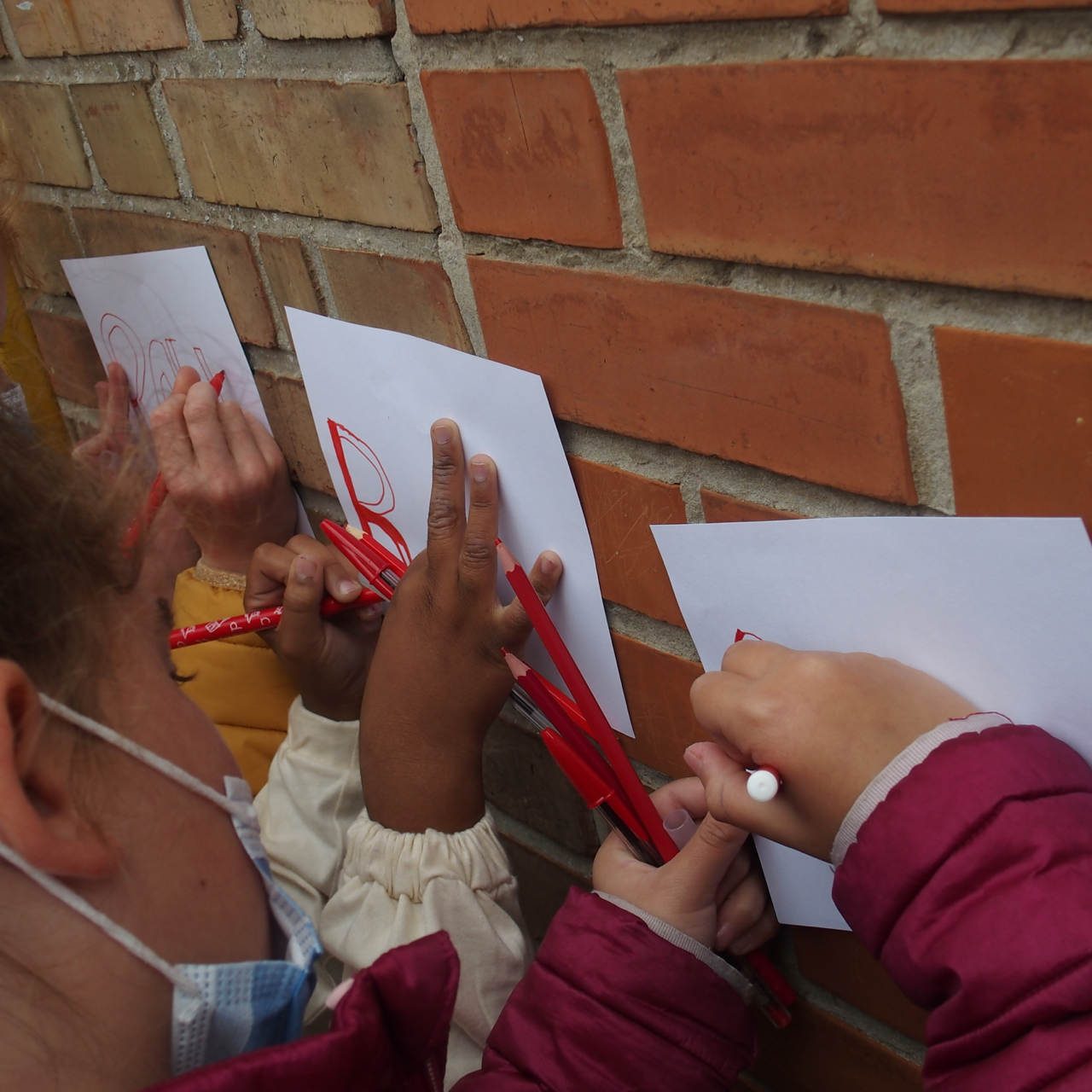
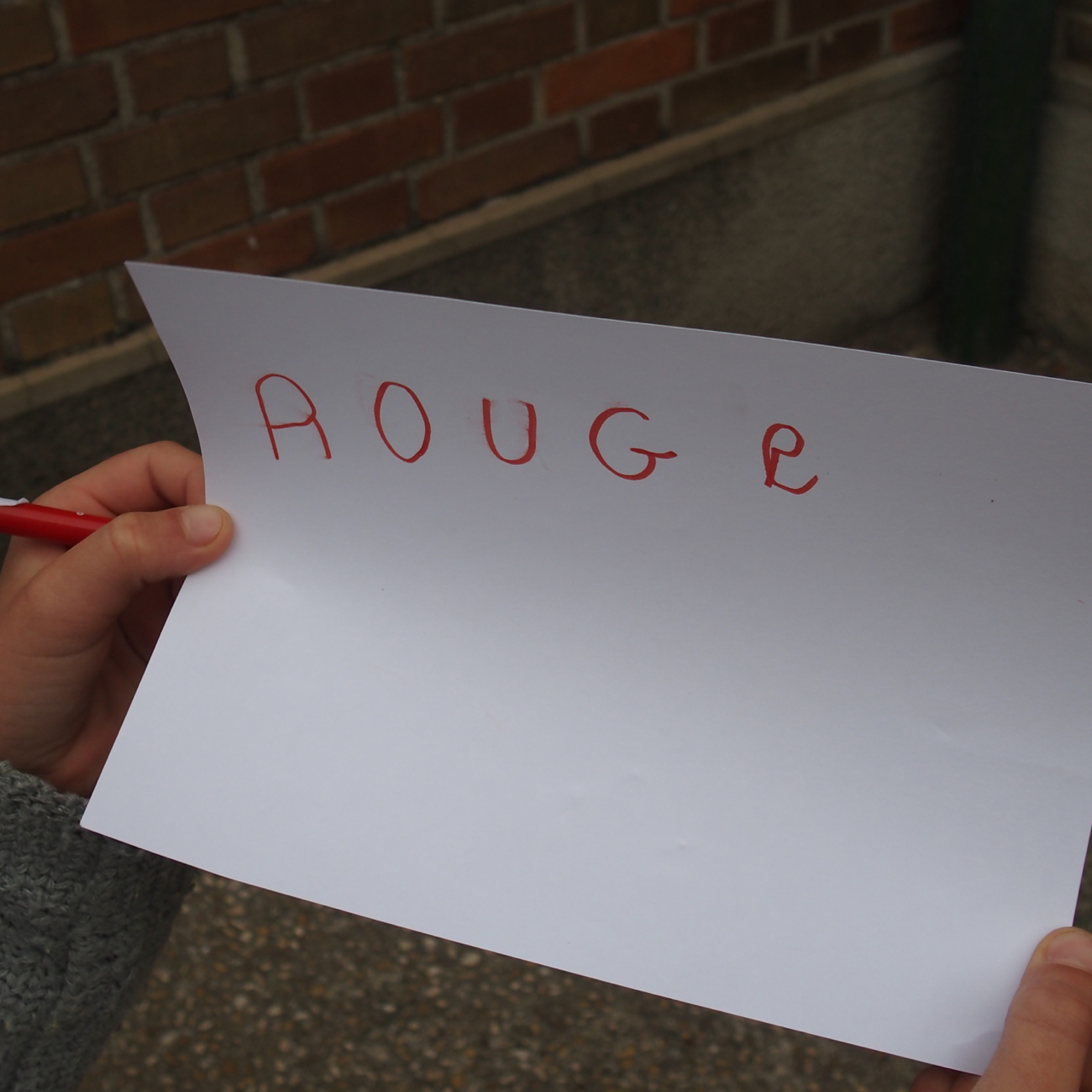
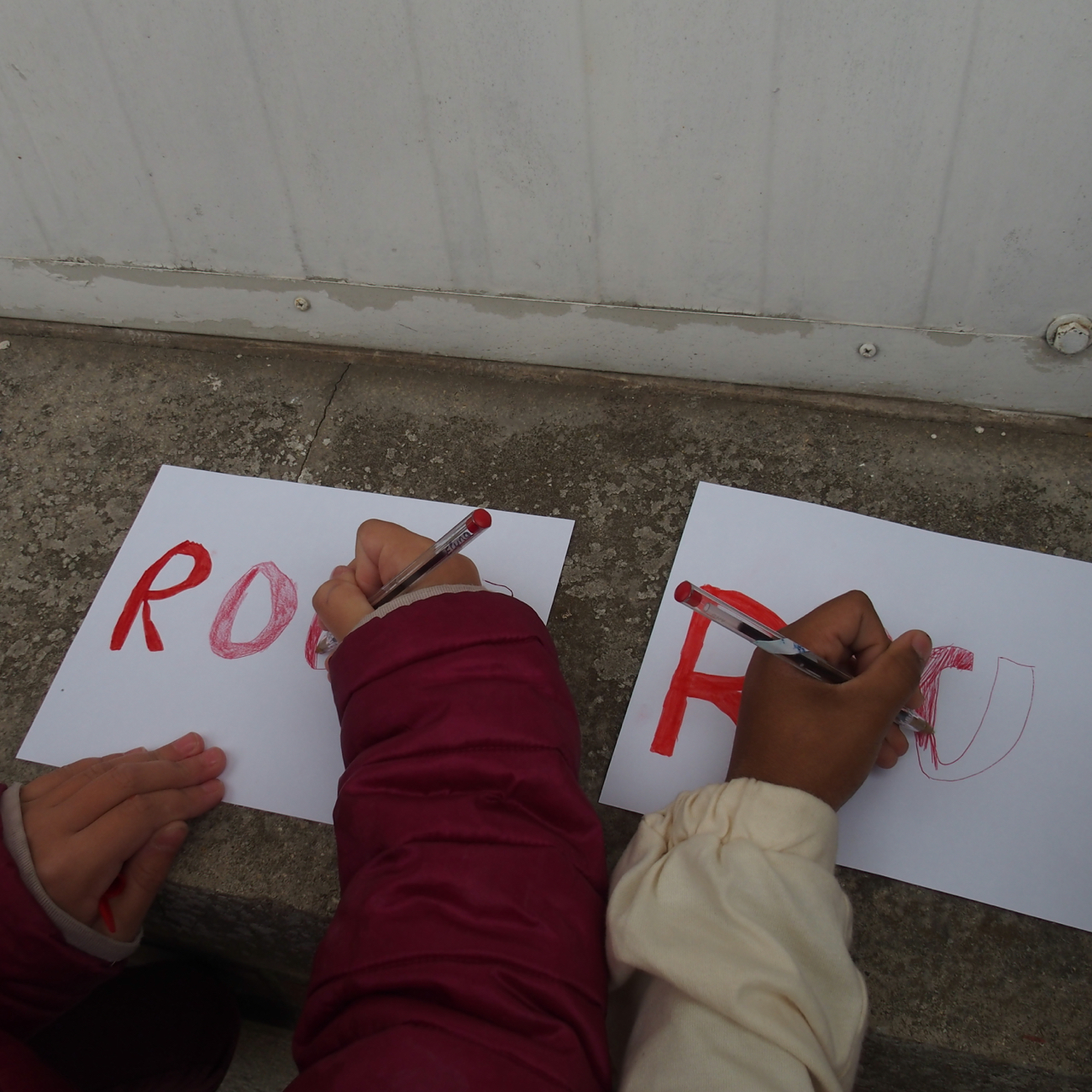
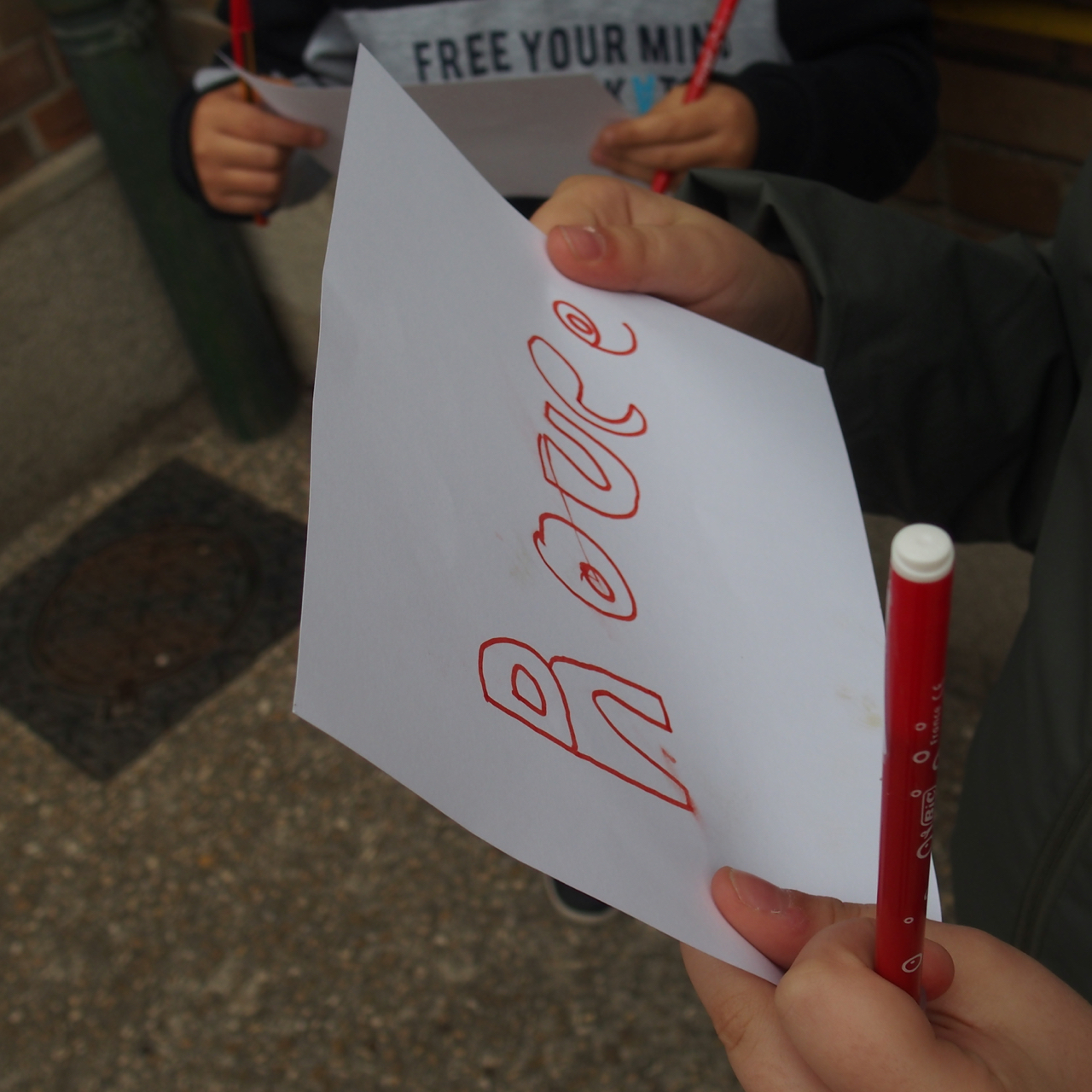
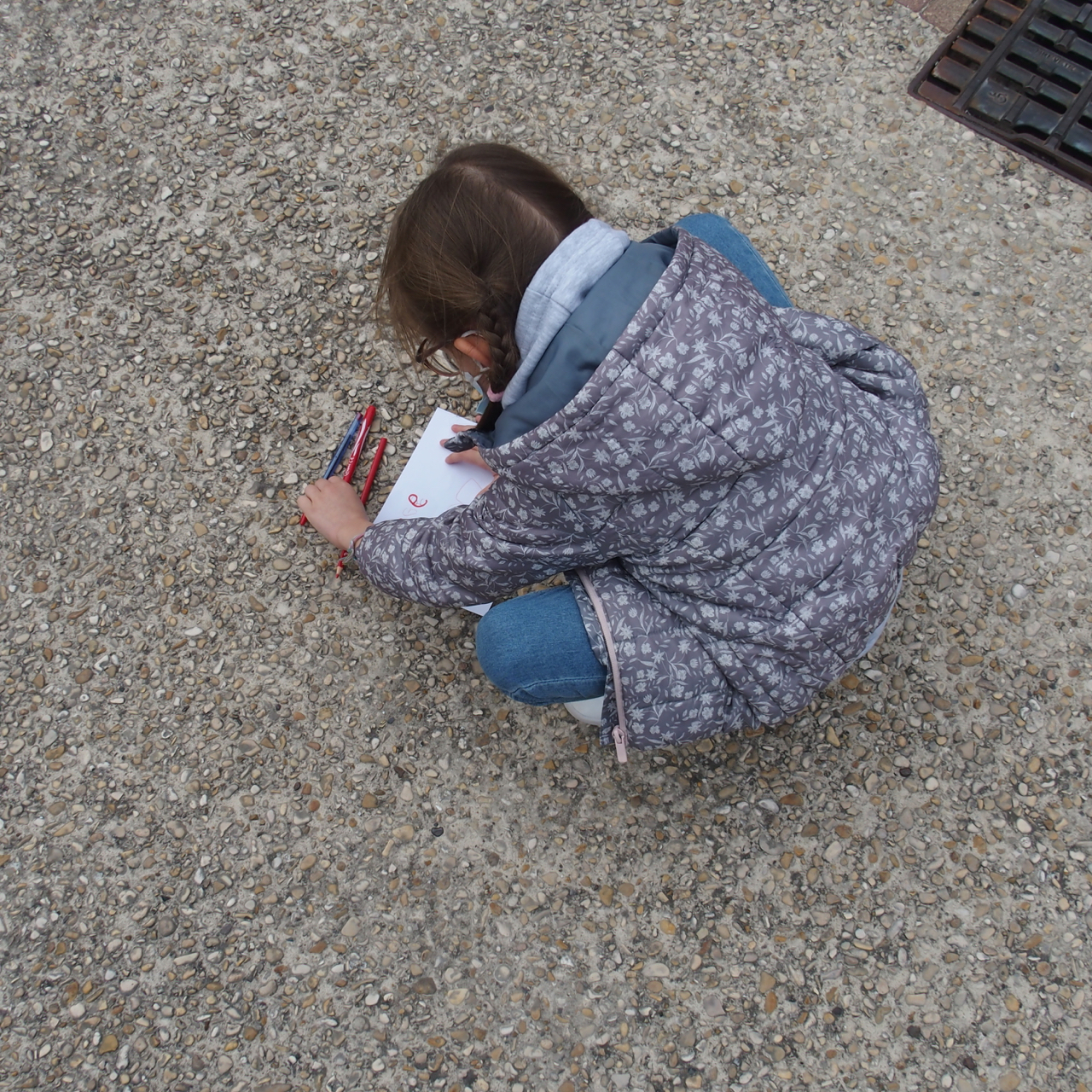
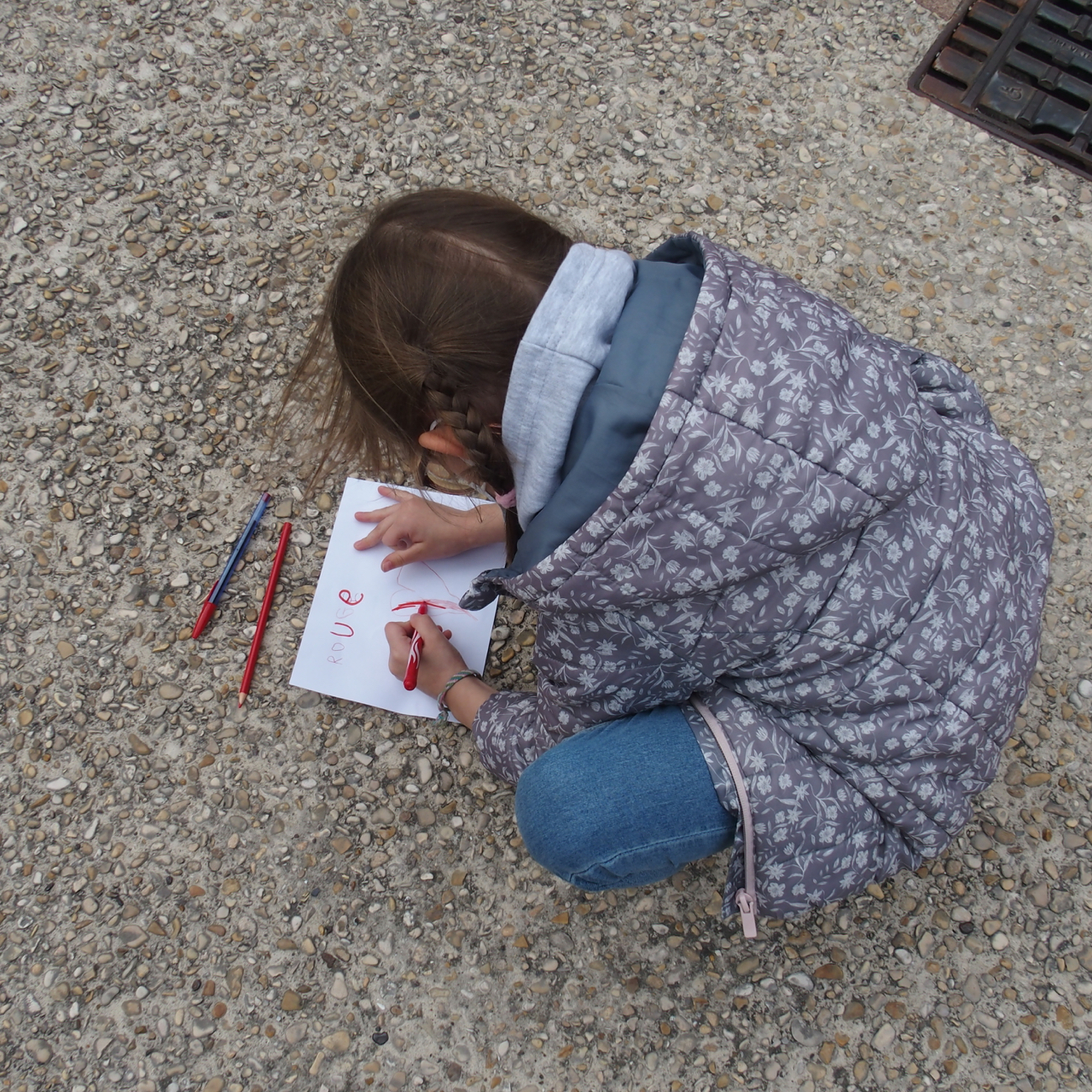
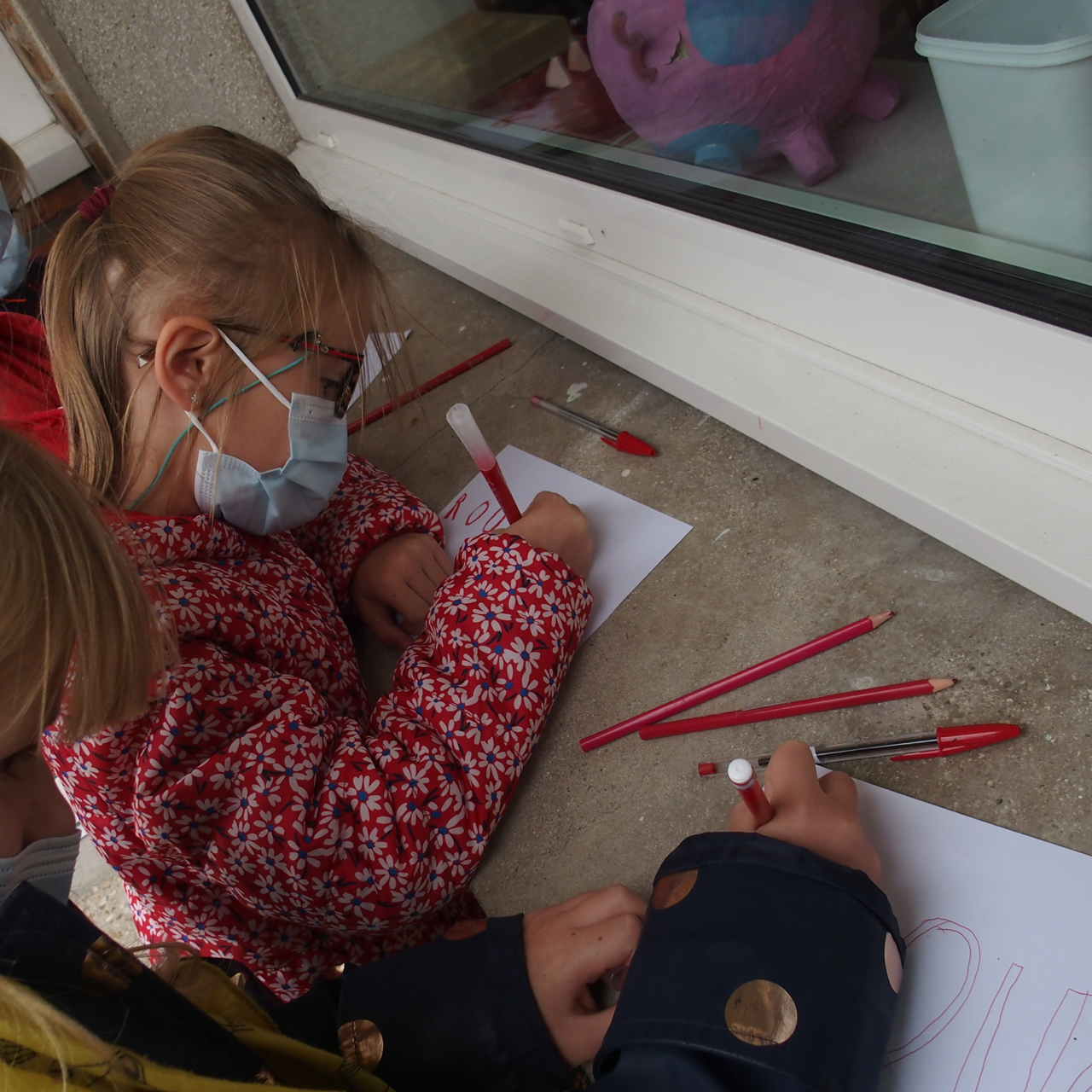
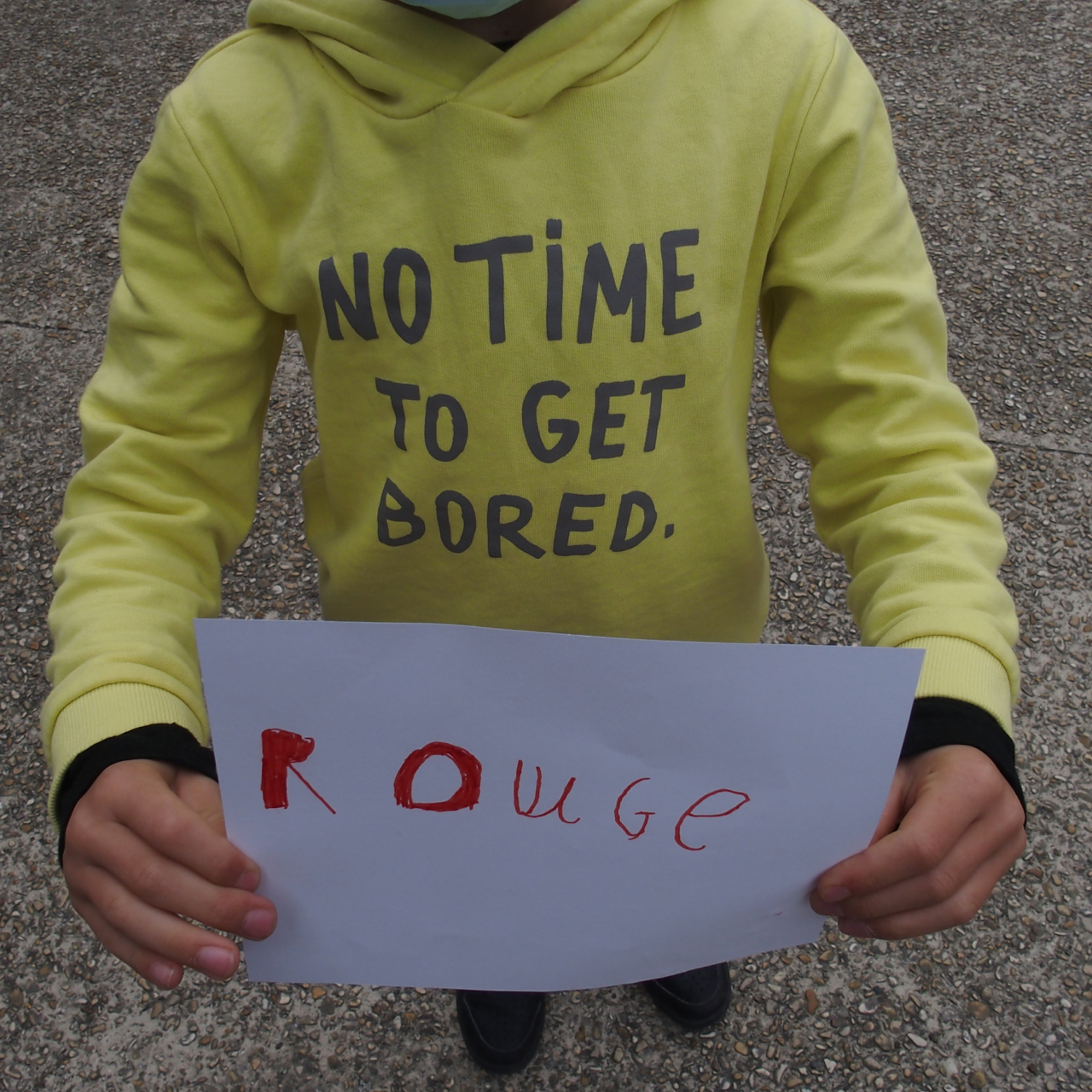
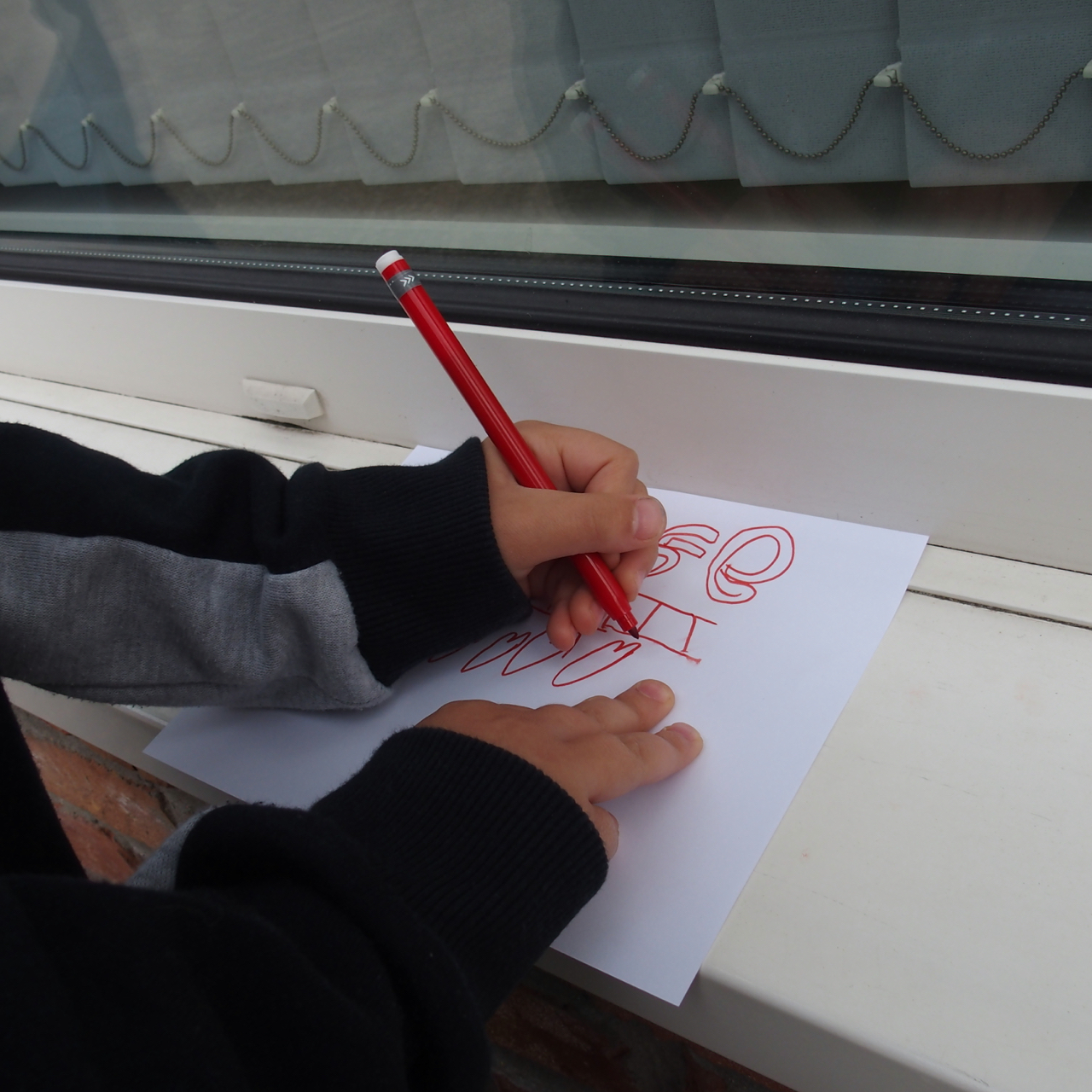
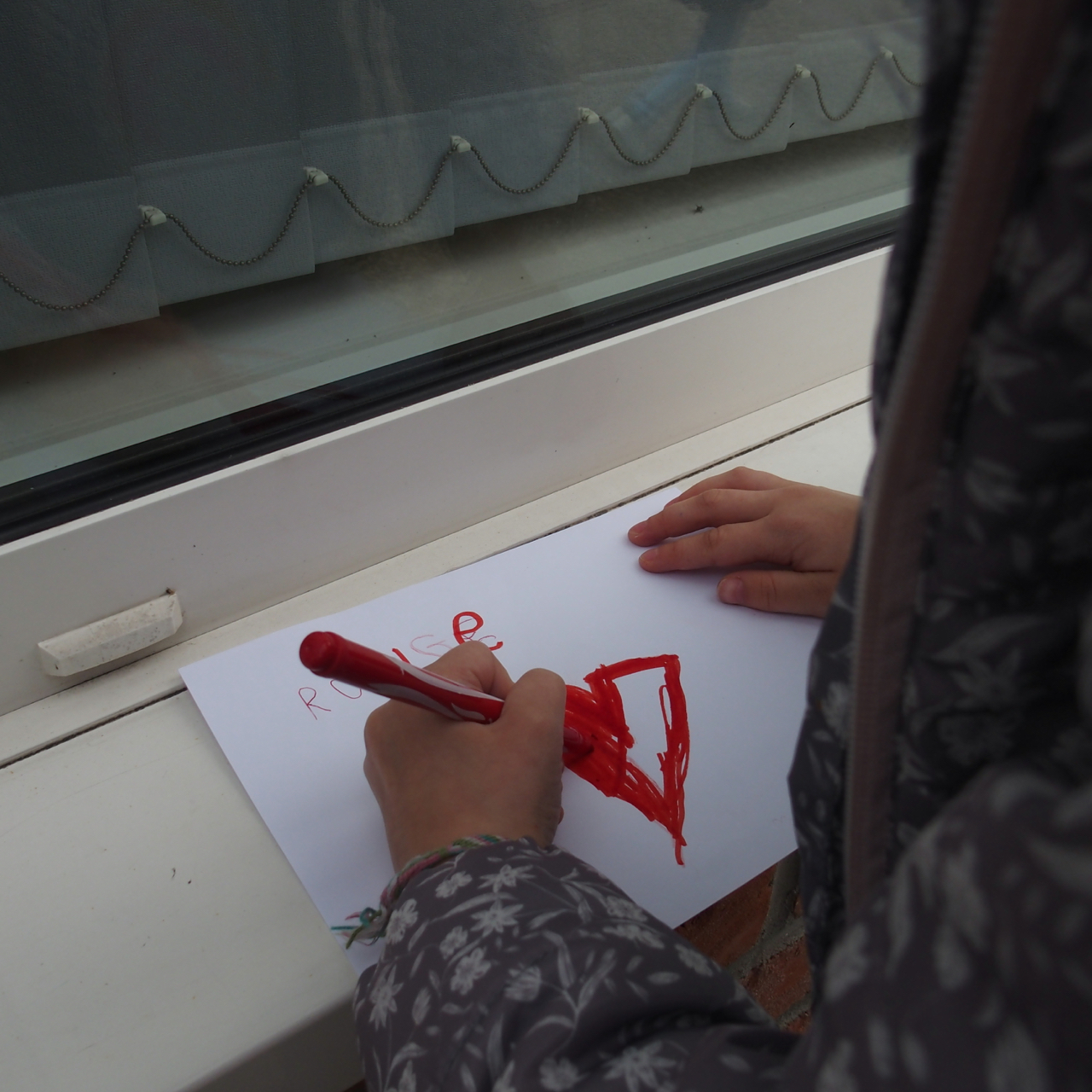
En grandissant, les dessins réalistes du ROUGE sont de moins en moins accompagnés de choses autour, associées au rouge. Des coeurs, des fusées, des maisons… ici en briques, rouges ( euh non limite: les maisons à Brouckerque sont en brique blanche sableuse de polder… ), bon il reste les toits, rouges, oranges.
Là, la chose qui me frappe, soudainement, dans cette classe, c’est le nombre d’enfants aux cheveux rou…x.
On retourne à l’abri quand la pluie se pointe, et me voici avec un groupe de graphistes plus que d’écrivains, composant de jolies abstractions lettristes. À moins que ce ne soit de la figuration ultralettriste!
La dernière fut création collective, chacun une lettre. Posée. Une après l’autre.
Le sixième atelier avec les tout-petits, j’étais tellement pris que je n’ai pas pris de photo.
La chanson de l’alphabet c’est hyper prenant…